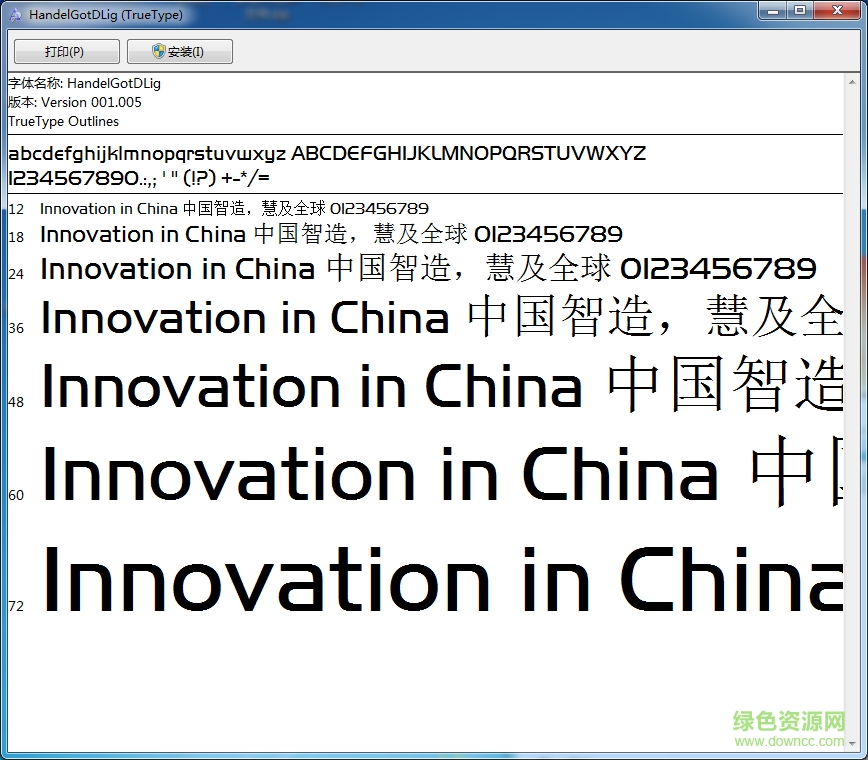
handelgotdlig
handelgotdlig是一款非常常用的英文字體,字體線條感十足,端正簡單大方如行云流水一般,使用便捷時刻彰顯個人魅力??靵砭G色資源網(wǎng)下載體驗吧!
handelgotdlig字體介紹
handelgotdlig字體是一款有著清新風格的英文字體,大氣簡潔的造型讓你的廣告設(shè)計、文字排榜更有特色,綠色資源網(wǎng)歡迎大家下載免費版!